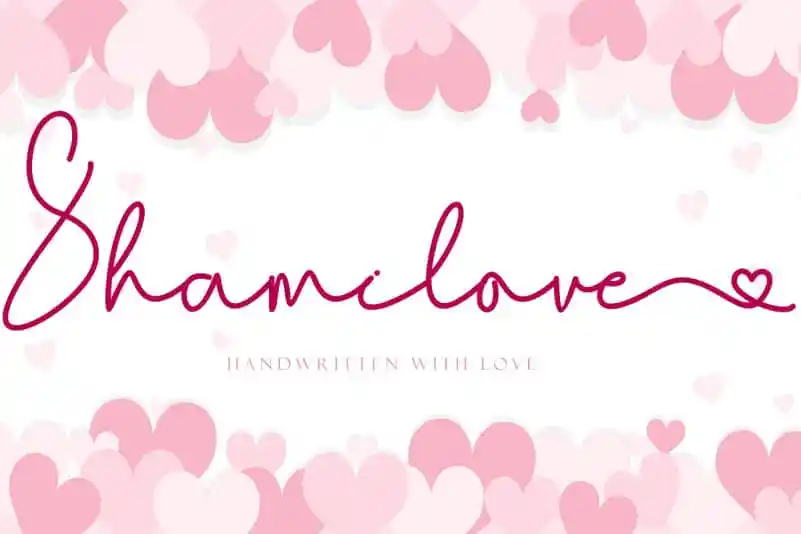
Shamilove Handwritten Font
A fonte ‘Shamilove Handwritten Font’ é uma escolha perfeita para aqueles que buscam transparência e delicadeza em seus materiais digitais. Com suas curvas românticas e sua forma de coração no final, essa fonte adiciona um toque amável às mensagens escritas ou aos logotipos. Convidamos você a experimentar o Shamilove Handwritten Font para criar mensagens que expressam sentimentos genuínos, especialmente em ocasiões como aniversários, casamentos e momentos de amor declarado. É perfeito não apenas para presentes românticos, mas também para promoções empresariais, postagens no Facebook ou qualquer outro tipo de material onde uma mensagem agradável é essencial. Não hesite em explorar Shamilove Handwritten Font – ele irá tornar sua presença online ainda mais única e significativa.